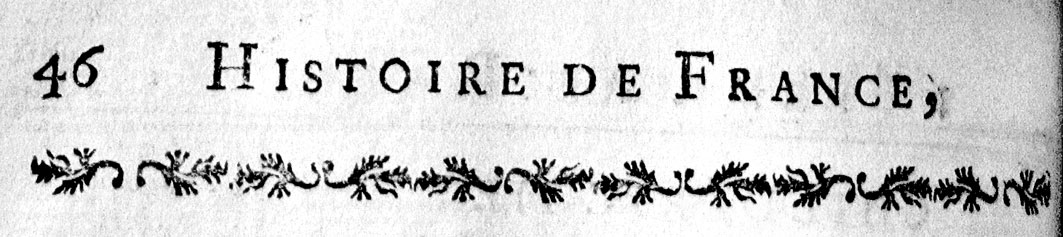
- Subject: Re : [typo] Cherche « grecque » en typo
J'ai feuilleté mes vieux livres, et voici ce que j'ai trouvé :
frise.jpg : Ce n'est pas vraiment une frise de pur type E, mais plutôt un mélange de genres ! Les deux derniers éléments de la frise sont bien renversés à 180°. Extrait du Nouvel abgégé chronologique de l'histoire de France, nouvelle édition, à Paris chez Prault père et autres, 1768, tome I.
voiture.jpg : la frise devrait correspondre à vos attentes, il y a juste une rupture de la série dans son milieu. Extrait de Les uvres de monsieur Scarron, reveuës; corrrigées (sic) & augmentées de nouveau, tome premier, à Paris chez Michel David, 1709.
helene.jpg : ici c'est le cul de lampe qui est à la grecque, mais les ratiches de la belle le sont aussi, je n'ai pas pu m'empécher de laisser le texte complet de ce sonnet de Scarron. Même livre que précédemment.